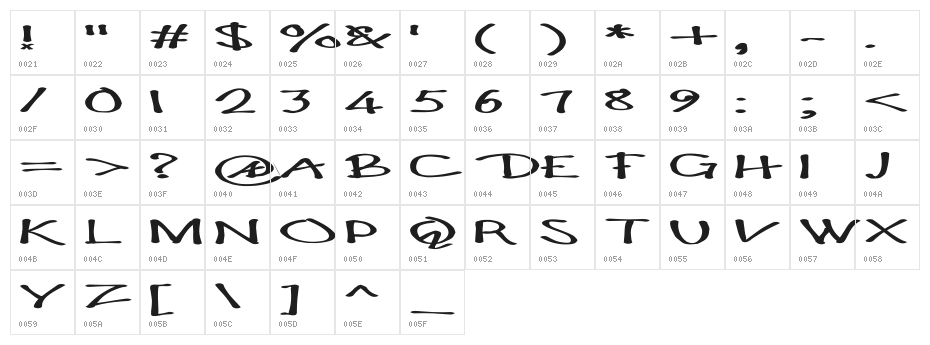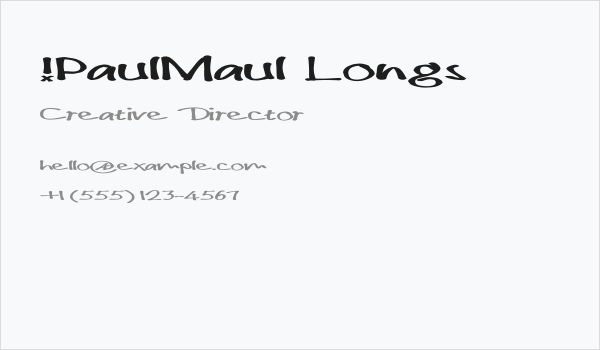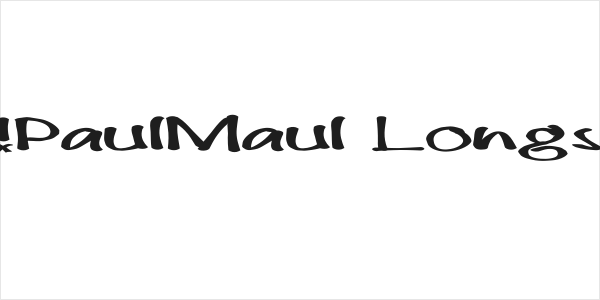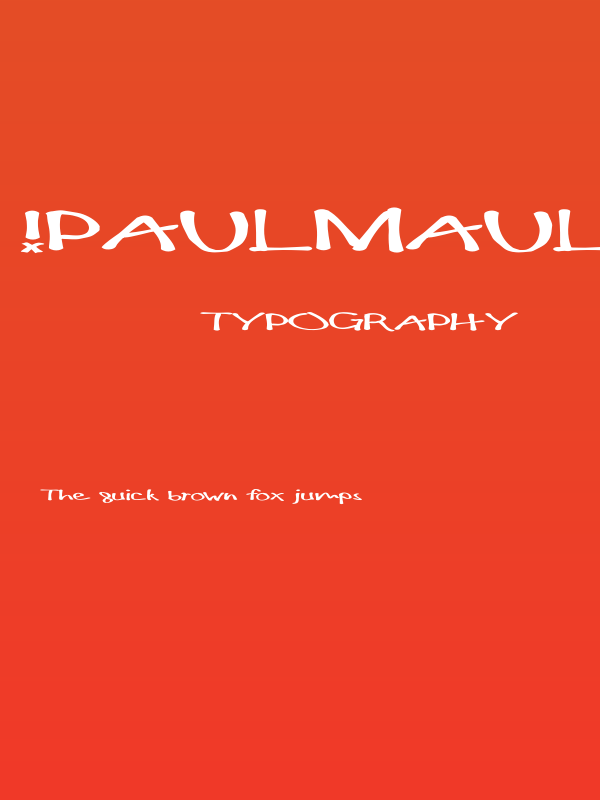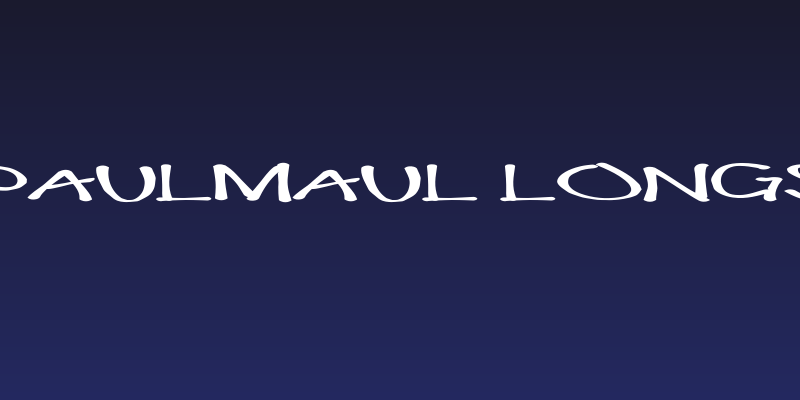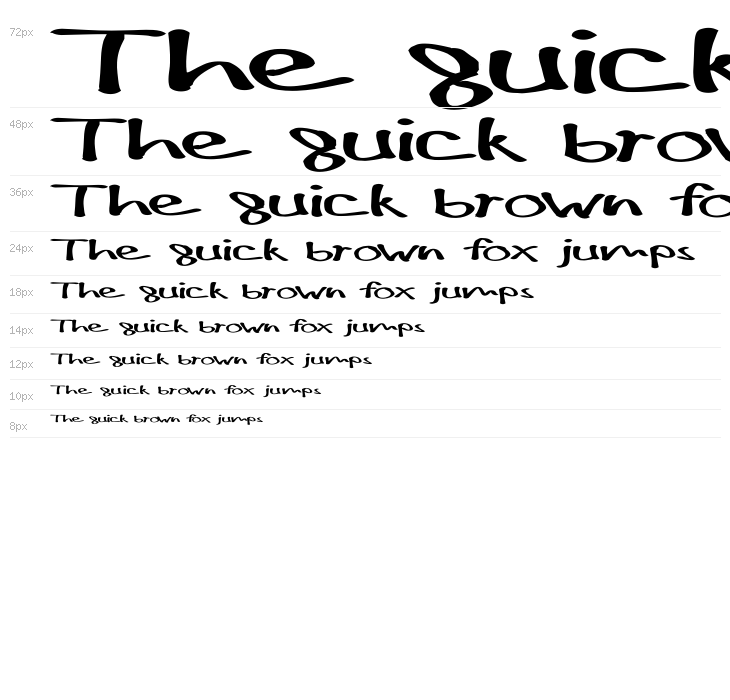
!PaulMaul Longs Font
| Progetti proposti | Ideal for creative projects such as logo design, branding, invitations, and posters where a lively and expressive touch is desired. |